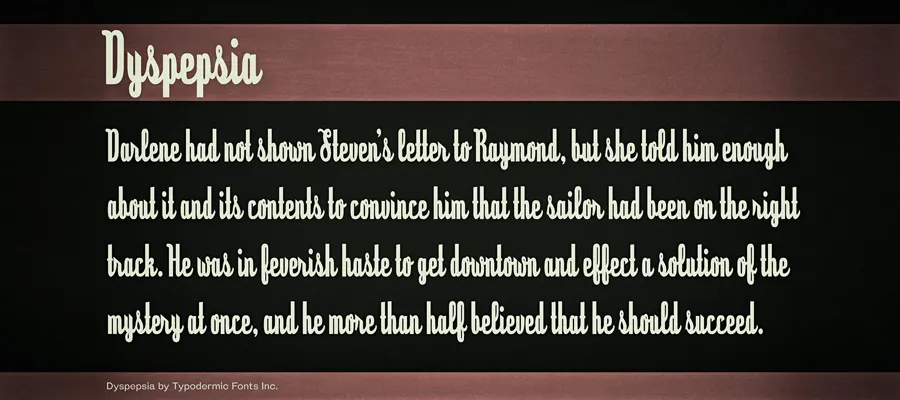
Dyspepsia é uma fonte de display vertical criada pelo designer Hamilton que mantém um tom elegante e distinto. Suave e sofisticado ao mesmo tempo, esta fonte foi projetada para atender a um vasto leque de usos gráficos. É perfeita para aplicativos como logotipos, posters, camisetas customizadas ou marcas no ambiente de loja, onde sua elegância e modularidade irão capturar atenção e deixar uma impressão imediata. Suas linhas curvadas e riscos sutis criam um charme que contrasta com seu design vertical e construído, oferecendo um contraste interessante em qualquer projeto. Com características flexíveis e versáteis, Dyspepsia está à altura de projetar desde uma identidade visual completa até peças detalhadas para a web. Hamilton criou esta fonte para levar o design gráfico ao próximo nível, fornecendo aos designers um recurso versátil que pode se adaptar a qualquer estilo ou projeto. Dyspepsia não apenas reúne as necessidades de um designer em uma única fonte, mas também oferece o poder e a liberdade para criar e personalizar mensagens com riqueza e sutileza, tornando-a um recurso indispensável para designers amadores e profissionais.